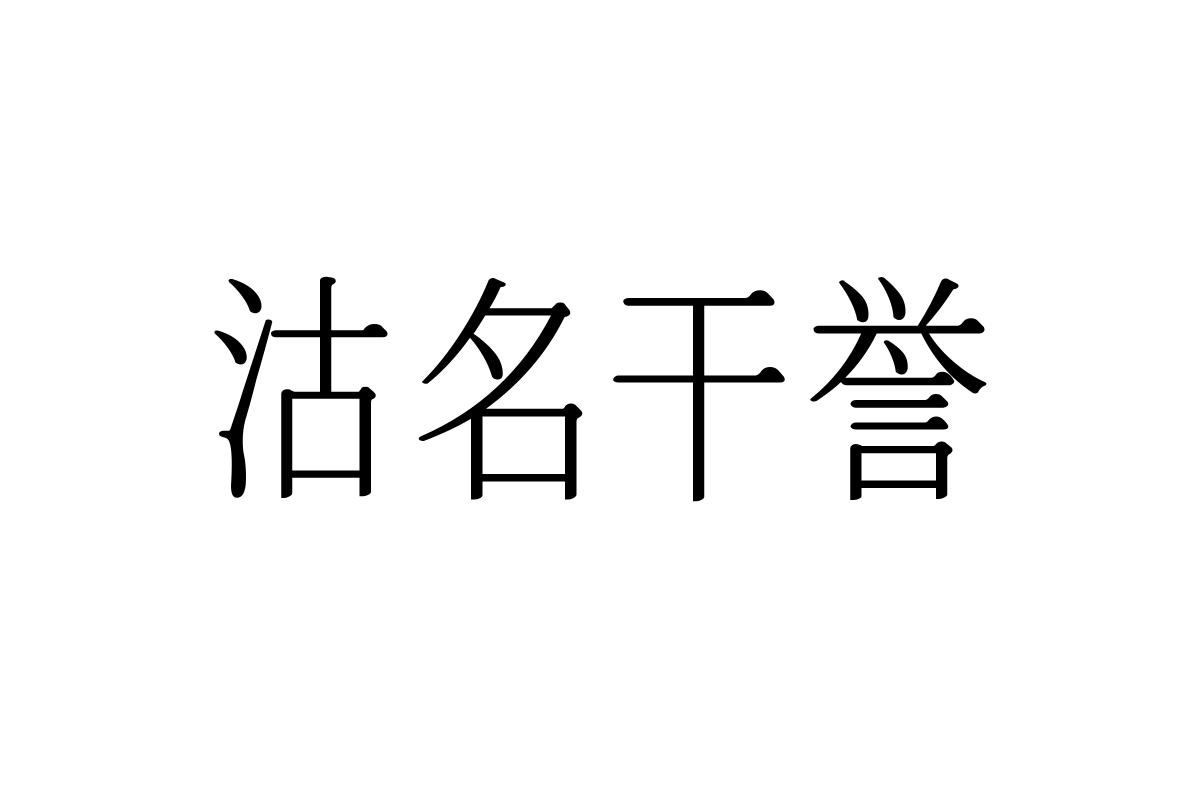
也字工厂思美人宋体是一款具有独特风格的中文字体,其特点是字形优美、线条流畅。这款字体适用于各种需要展示文字的场合,如网页设计、平面设计、广告设计等。
也字工厂思美人宋体的特点如下:
1. 字形美观:这款字体的字形设计独特,线条流畅,给人一种优雅的感觉。
2. 笔画清晰:每个字的笔画都清晰可辨,易于阅读和识别。
3. 风格独特:这款字体的风格独特,既有传统的韵味,又不失现代感,适合各种设计风格的应用场景。
4. 适用范围广:无论是在网页设计、平面设计、广告设计还是其他需要展示文字的场合,都可以轻松使用。
总的来说,也字工厂思美人宋体是一款非常适合用于各种设计场景的中文字体,无论是在视觉美感还是实用性方面都能满足用户的需求。